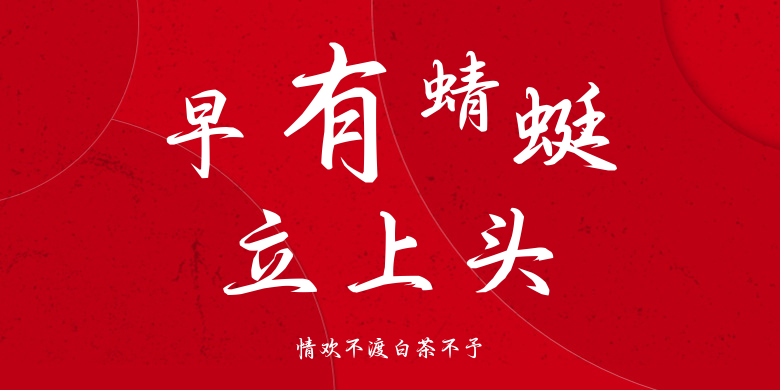
情欢不渡白茶不予
情欢不渡白茶不予,这款字体结构工整、笔画清晰,兼顾美观与易读性,适用于标题、正文、海报、包装、LOGO 等多种场景。字形优雅稳定,风格百搭耐看,适配日常排版与创意设计,让文字呈现更舒适、更具质感。情欢不渡白茶不予一笔一画,皆是细节,以均衡的比例、流畅的线条打造舒适视觉体验,字形端正大气,风格简约现代。无论是商业设计、品牌宣传还是日常排版,都能轻松驾驭,让文字更有格调与力量。情欢不渡白茶不予字体下载。